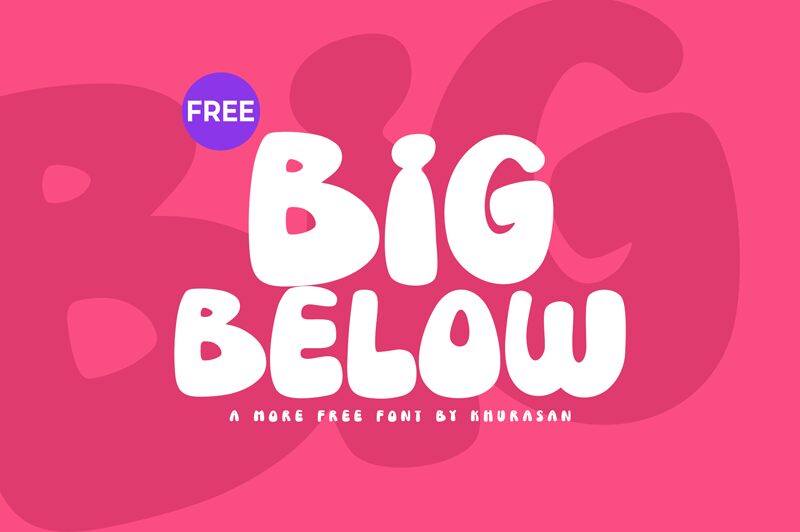
Bigbelow von Khurasan ist eine kostenlose, klobige Cartoon-Display-Schrift mit übergroßen, bauchigen Buchstaben und einem charmanten, handgezeichneten Schwung. Ihre schweren Formen, abgerundeten Ecken und unebenen Konturen erzeugen einen verspielten, Sticker-artigen Rhythmus mit einem leichten Gefühl von Bewegung.
Diese kostenlose Schriftart eignet sich hervorragend für Kinderbuch-Cover, Snack-Verpackungen, Spielzeug-Branding, Party-Poster und animierte Titelkarten. Die breiten, schwungvollen Großbuchstaben wirken am besten in kurzen Überschriften, wo ihr enger Zeilenabstand und die unregelmäßigen Silhouetten die gesamte Komposition tragen können.